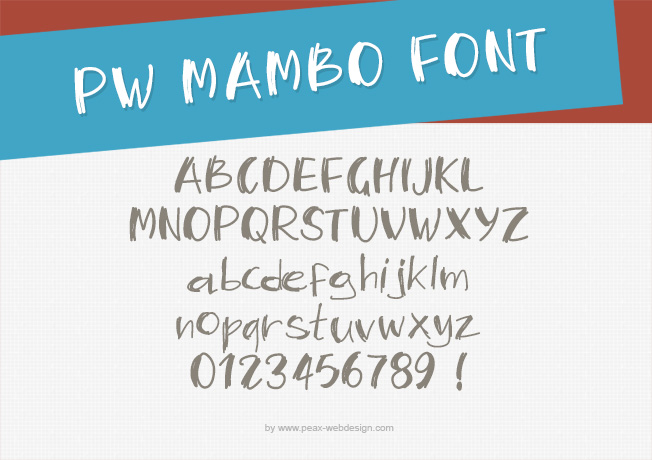
PW Mambo, police manuscrite au format .ttf.
PW Mambo, une typo publiée ce jour d'éclipse solaire. Elle n'a pourtant aucun rapport avec cet événement, c'est simplement une police de caractères manuscrite, dédoublée par endroits pour créer un épaississement qui lui donne un style particulier. A utiliser sans modération. Pour un usage commercial, merci de me contacter.